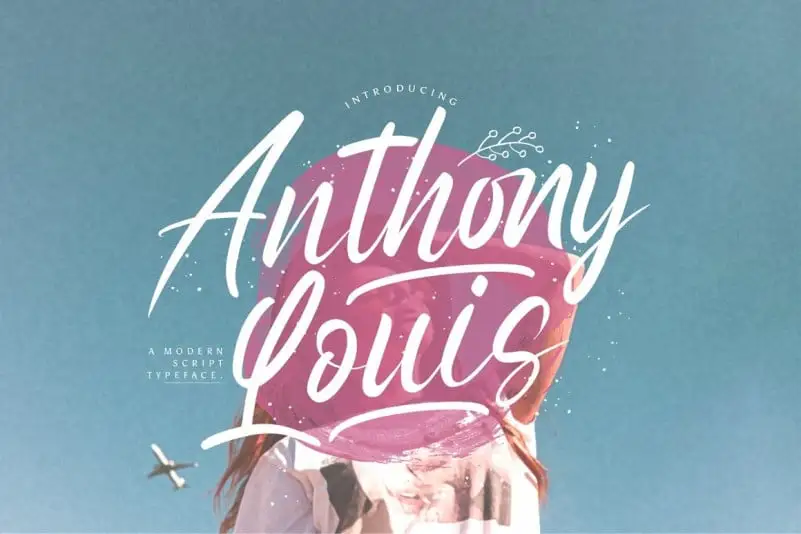
Anthony Louis Script Font – Download Grátis
A Anthony Louis Script Font é uma fonte script poderosa que explode com energia. Concebida pelo designer StringLabs para 99designs, ela tem o poder de transformar um amplo espectro de projetos de design em níveis muito altos, desde identidades visuais e títulos até designs de casamentos, convites, assinaturas, logotipos e rótulos. O facto de ser PUA (Unicode) codificado significa que você pode facilmente acessar todos os gílios e swashes da fonte sem esforço. Uma escolha perfeita para designers em busca de um visual arrojado e vibrante, a Anthony Louis Script Font está pronta para revolucionar seus projetos gráficos.